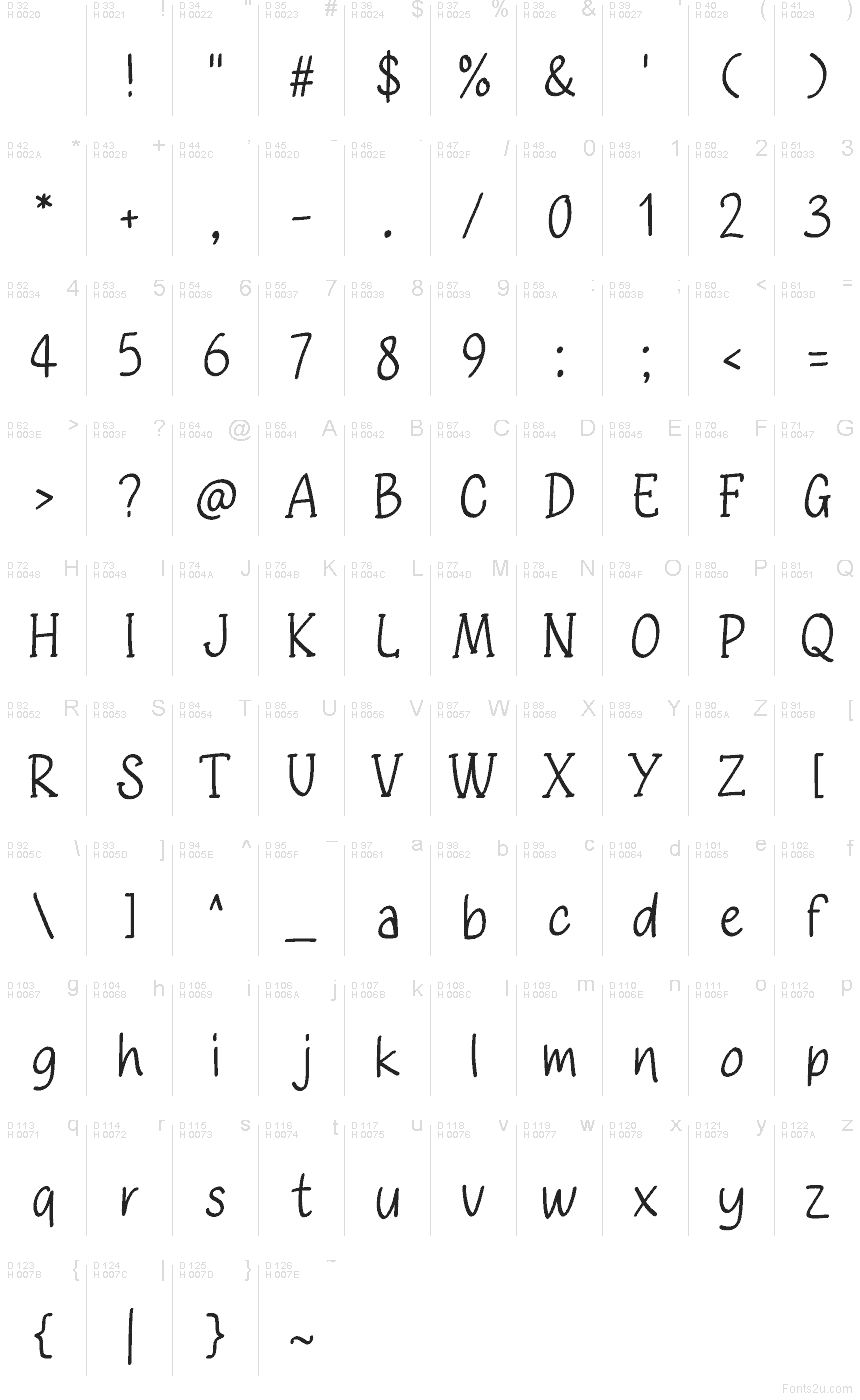
Chocolate Burn
Шрифт Chocolate Burn від Hello Good Studio — це безкоштовний рукописний шрифт з високими, розслабленими вигинами та плавним, легким ритмом. Літери зберігають невимушений «ручний» стиль, а заокруглені з'єднання та відкриті форми надають написам м'якості та індивідуальності.
Chocolate Burn чудово підходить для карток із рецептами, меню кафе, пакування, цитат, графіки для соціальних мереж та етикеток для виробів ручної роботи, оскільки його вільний скриптовий стиль виглядає неформально, але охайно. Цей безкоштовний шрифт також гарний для невеликих акцентів у логотипах та деталях запрошень, коли вам потрібен текст, що виглядає по-справжньому живим і легко вписується в макет.